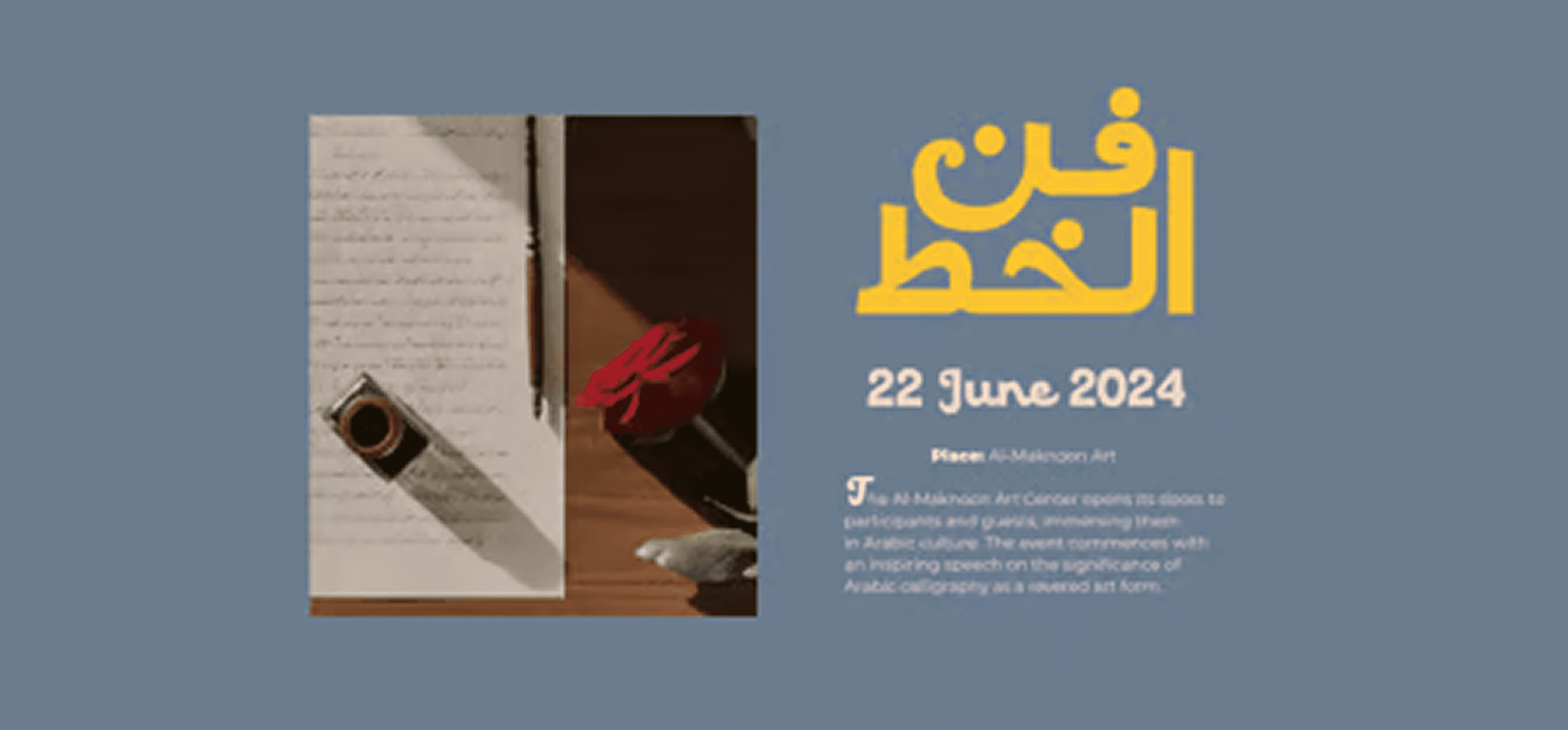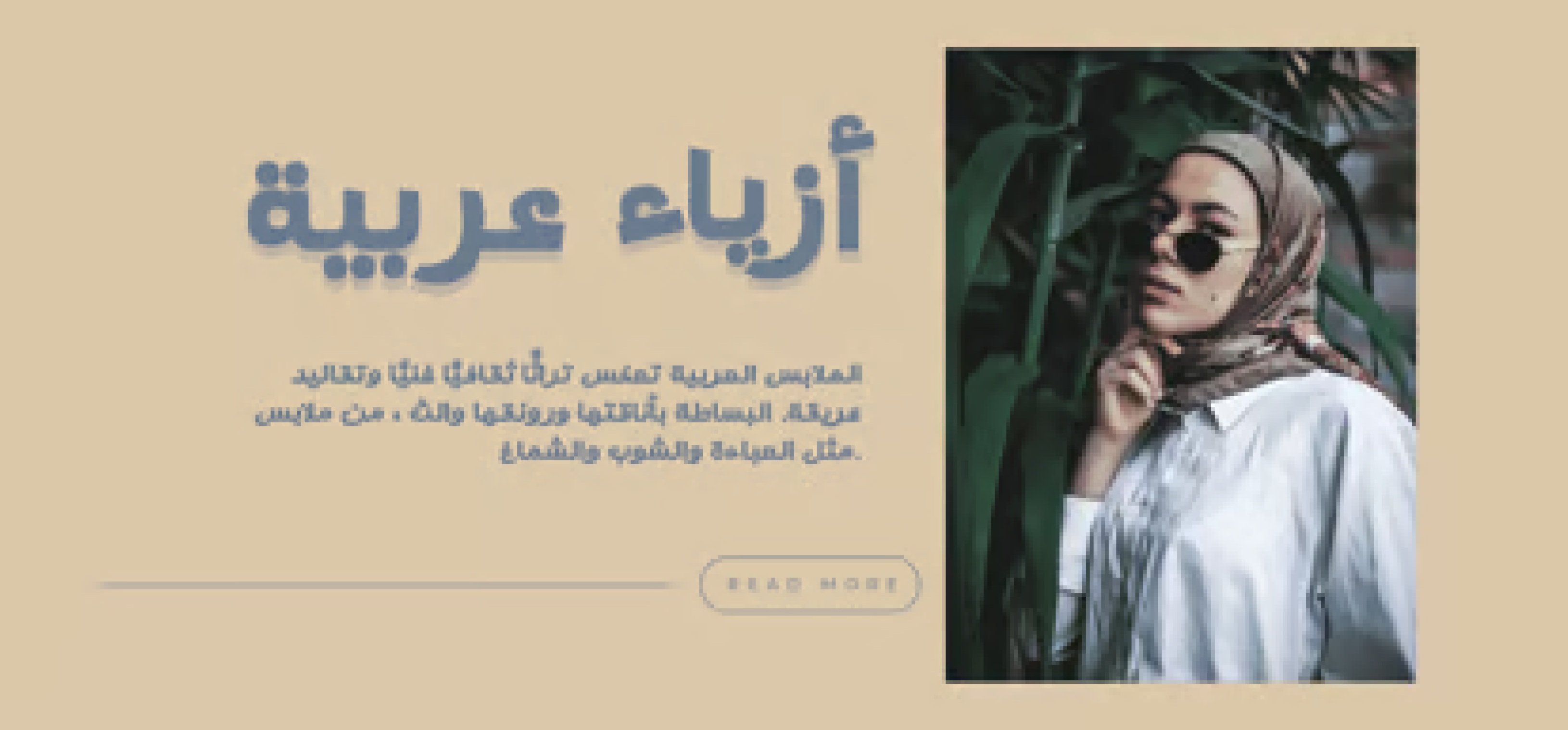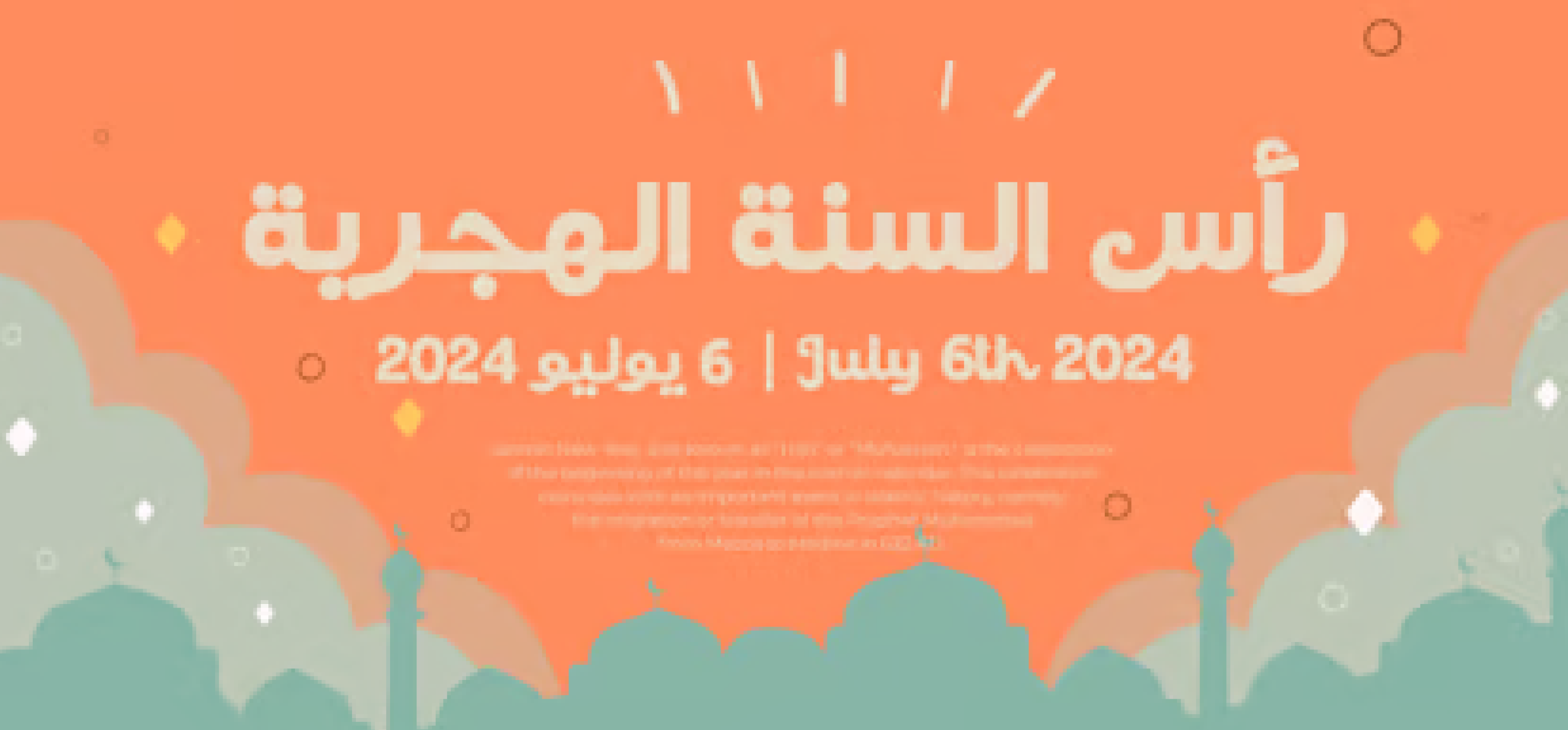
انغمس في تفاصيل خط الغرّاف الآسرة، وهو خط عربي يدمج بسلاسة بين جماليات الخط العربي الأصيل وحيوية التصميم العصري.
تحكي كل انحناءة وتفصيل فيه قصص الصحارى القديمة والأسواق النابضة بالحياة، ورغم جذوره التراثية، فإن ملامحه الحادة والواضحة تمنحه حضورًا عصريًا لافتًا.
خط الغرّاف هو توازن بين الماضي والحاضر، يُضفي على تصاميمك طابعًا مميزًا يجمع بين الأصالة والحداثة.